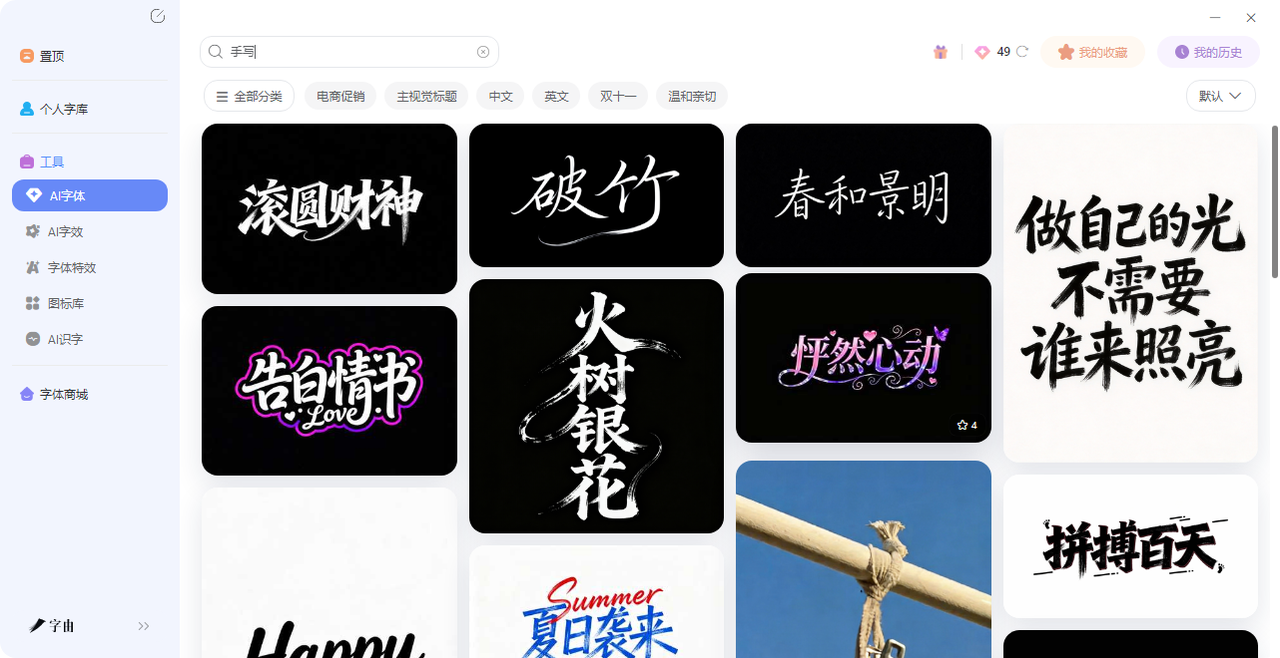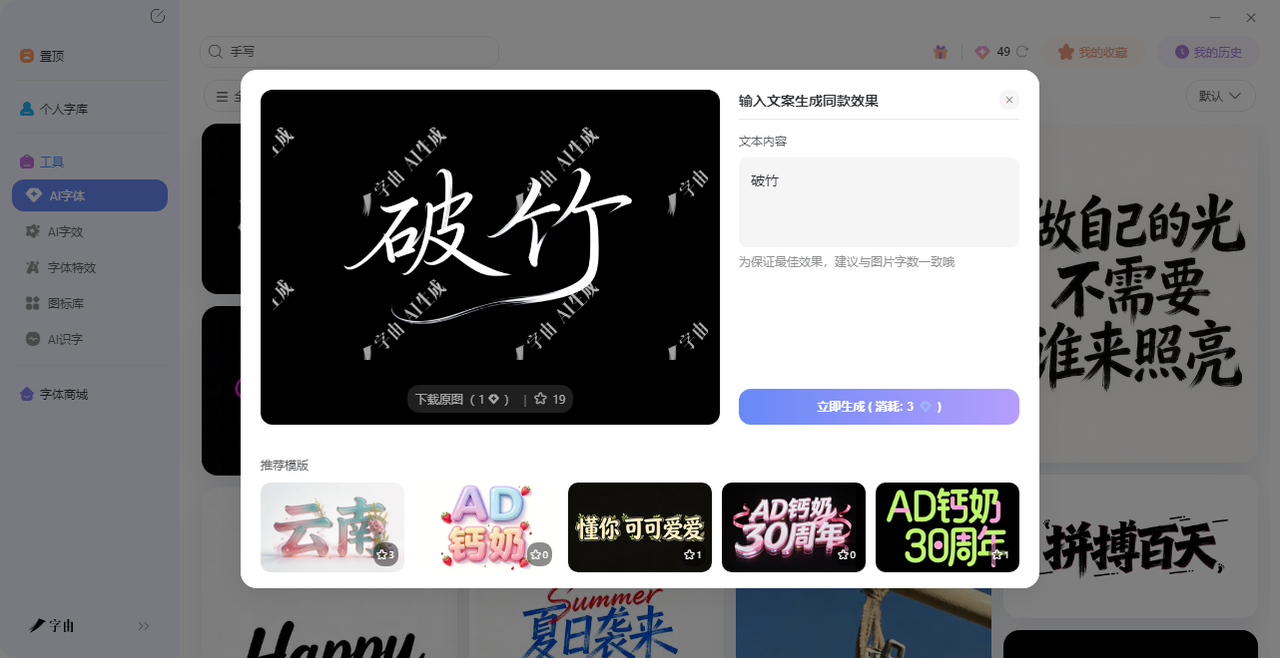
手写字体在线生成器推荐,打开网页就能立刻用
相信你有过做手账的时候,但是会担心自写不好看而影响画面整体,除了手账本,生活中也会遇到很多用到手写字体的时候,不过大部分都是手写功底跟不上想法。其实,这个问题早就有解了——现在有不少手写字体在线生成器,打开网页,输入文字,就能立刻生成各种风格的手写体。今天就把我私藏的5 个手写字体在线生成器整理出来,方便大家使用。
字由的“AI字体”功能,是我用过最顺手的手写字体在线生成器。它不只是一个字体库,更是一个能直接生成手写艺术字的工具。你不需要会书法,也不用懂设计,输入文字,选个手写模板,几十秒就能拿到一张逼真的手写体图片。
接下来我会教大家如何使用字由的AI字体:
第一步:打开字由客户端或网页版,进入【AI字体】页面。在搜索框里输入“手写”“毛笔”“墨迹”“笔触”,系统会筛出一批带着手写痕迹的模板。这些模板不是单纯的字体,而是把文字做成了像用毛笔、钢笔、水彩笔写出来的效果——有墨迹的浓淡,有笔锋的飞白,有纸纹的肌理。
第二步:每个模板都有预览图,点进去能看到细节。比如有一个模板模仿毛笔行书,笔画连笔很流畅,边缘有飞白效果;另一个像蘸水钢笔写的小字,清秀工整。选好模板,把模板里的示例文字换成你自己的文案(比如“春日来信”“见字如面”),最好和模板字数保持一致。这些模板的分类很细:做手账有“手账风”,做贺卡有“温馨手写”,做书法标题有“毛笔行书”。每个模板还支持微调——可以改颜色、调背景、甚至调整文字的倾斜角度。不满意就换一个,总有一款能对上你的感觉。
第三步:生成之前,还可以在编辑页面里微调文字的位置和大小。如果模板字数和你文案不一样,AI也会尽量适配,但效果最好的还是字数一致的。每天有免费算力点,不够用的话1 元买10 点,试错成本很低。点“立即生成”,等20-30秒,就能拿到一张带手写效果的艺术字图片。下载时选透明背景,直接拖进手账APP、PS、Canva里用,不用抠图,不用调色。如果不满意,换个模板重新生成,都没关系。
然后如果还是不知道搜什么关键词的话我可以给大家推荐几个我常用的关键词,搜索出来的每一个模板都很实用:
- 毛笔行书:笔画连笔,有飞白,适合写古风句子、诗词
- 钢笔手写:线条细,工整清秀,适合写日常笔记、信笺
- 水彩笔触:边缘晕染,带水痕,适合做手账标题、文艺封面
- 硬笔手写:像中性笔写的,自然随意,适合生活记录
- 软笔楷书:介于毛笔和硬笔之间,圆润温暖
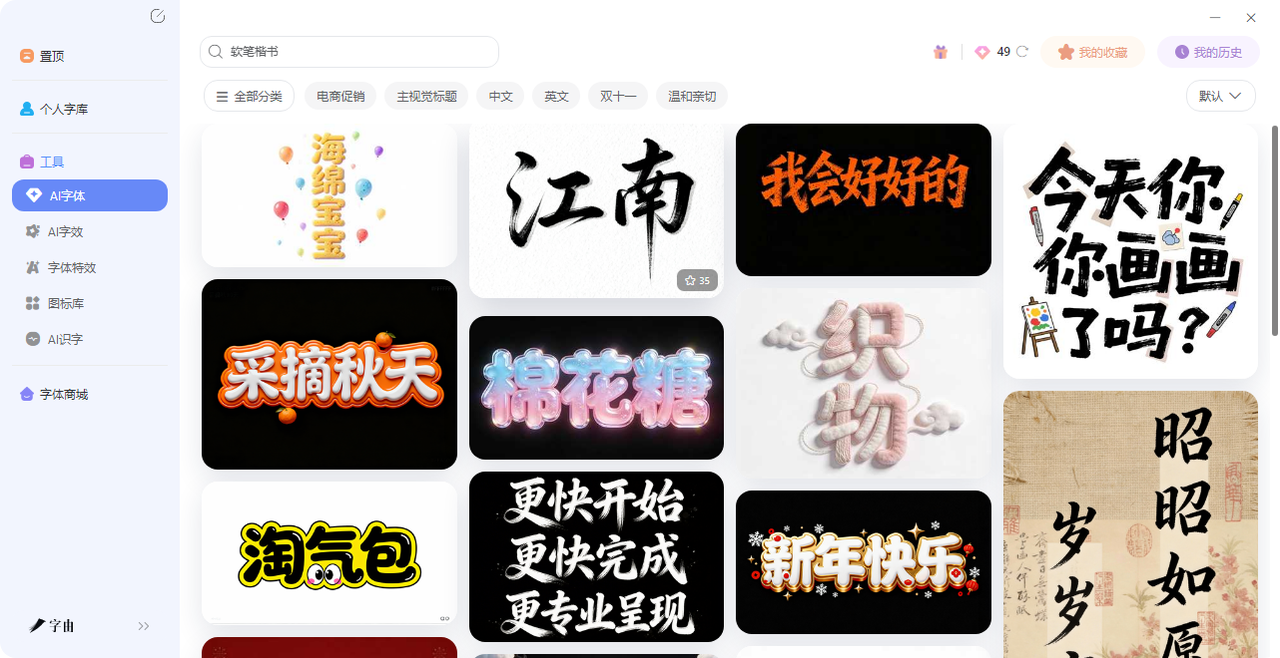
这些模板都不是基础字体,而是做好的特效效果。你不需要会书法,也不需要装字体,选个模板,填好自己想要的文案就可以了,整个过程十分简单。
2、Handwriting Font Generator
这个手写字体在线生成器提供了79 种手写样式,包括脚本体、粗体、斜体、无衬线手写等。界面左侧有样式分类,右侧是实时预览。操作也很简单:在输入框里打字,下面会自动显示所有样式的预览。你还可以调节文字大小、间距、颜色、背景,甚至加装饰、边框。喜欢的样式旁边有“Copy”按钮,点一下就能复制成Unicode 文本,直接粘贴到 Instagram、微信、微博里,不用存图片。适合需要快速把普通文字变成手写风社交文案的用户,完全免费,无需注册。比如你输入“生日快乐”,它会自动生成圆润的手写体、带花体的草书、还有像蘸水钢笔写的小字。每种风格都对应一个Unicode字符集,复制之后直接粘贴到任何地方,不会变形。
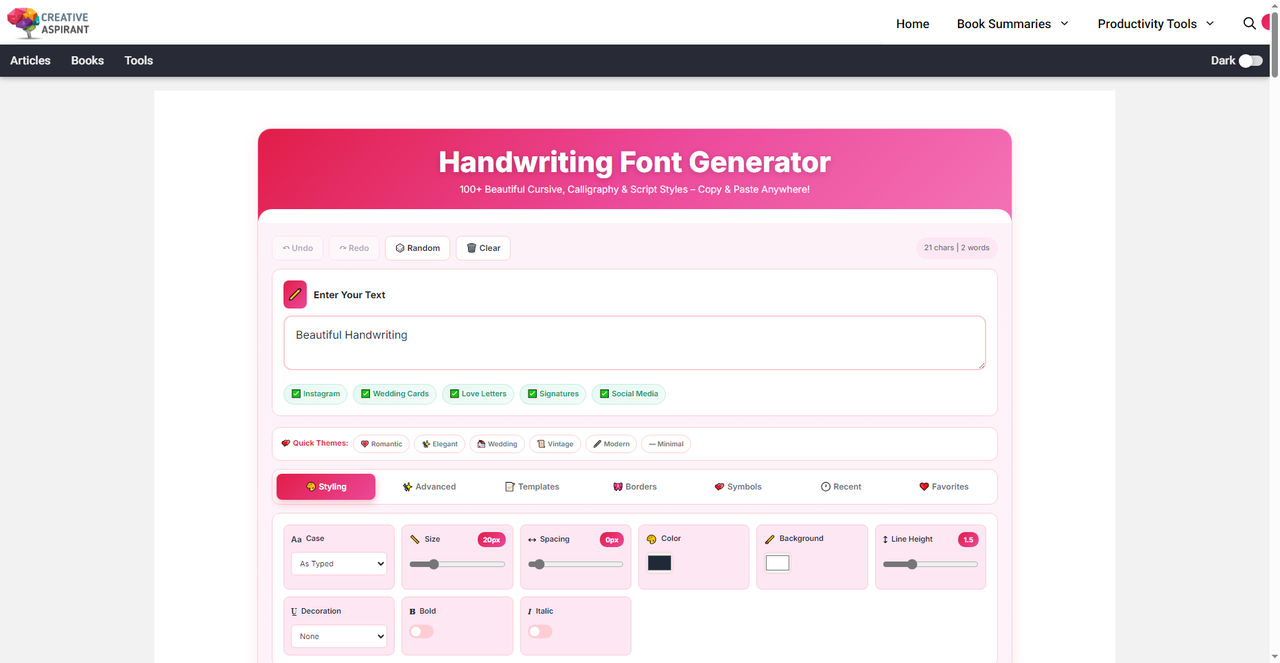
3、Fonts Generator
Fonts Generator 提供了50多种手写风格,分类有“Cursive”“Cute”“Bold”“Simple”“Decorative”等。输入文字,点击“Generate”,下面会列出所有样式,每个样式旁边有“Copy”按钮,复制后直接粘贴到任何地方。网站还提供了“Quick Themes”,比如“Romantic”“Elegant”“Wedding”“Vintage”“Modern”“Minimal”,可以快速筛选对应风格。如果你要做情书、婚礼卡片、复古海报,点一下主题就能找到合适的字体。比如点“Romantic”,出来的字体会带一点花体卷曲;点“Vintage”,字体会有复古的晕染感。每个主题下都有好几个样式,不用自己慢慢挑,一键就能找到氛围。
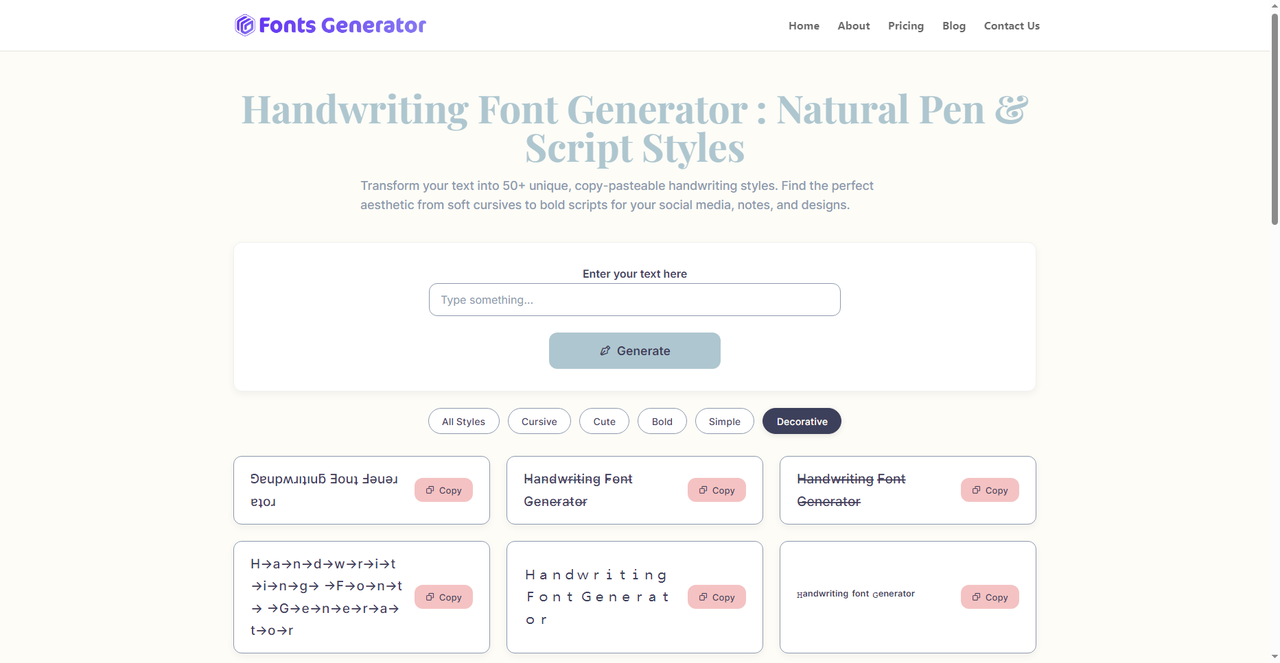
4、100LS Text to Handwriting
100LS 是一个更专业的手写字体在线生成器,专门用来把文字转换成逼真的手写文档。它有更多自定义选项:可以选择字体(比如Gloria Hallelujah),调整字体大小、墨水颜色(深黑、蓝色等),还可以选择纸张类型(白纸、横格纸、方格纸等)。生成后可以下载为图片或PDF。适合做手写笔记、作业、信件、证书等。它模拟了真实手写的效果,有墨迹深浅和纸张纹理,看起来很像真的手写。纸张类型有白纸、横格纸、方格纸、信纸四种。墨水颜色可以选黑色、蓝色、红色。生成前还能预览效果,满意了再下载。如果你做手写笔记,这个工具模拟的纸张纹理和墨迹渗透感很真实。
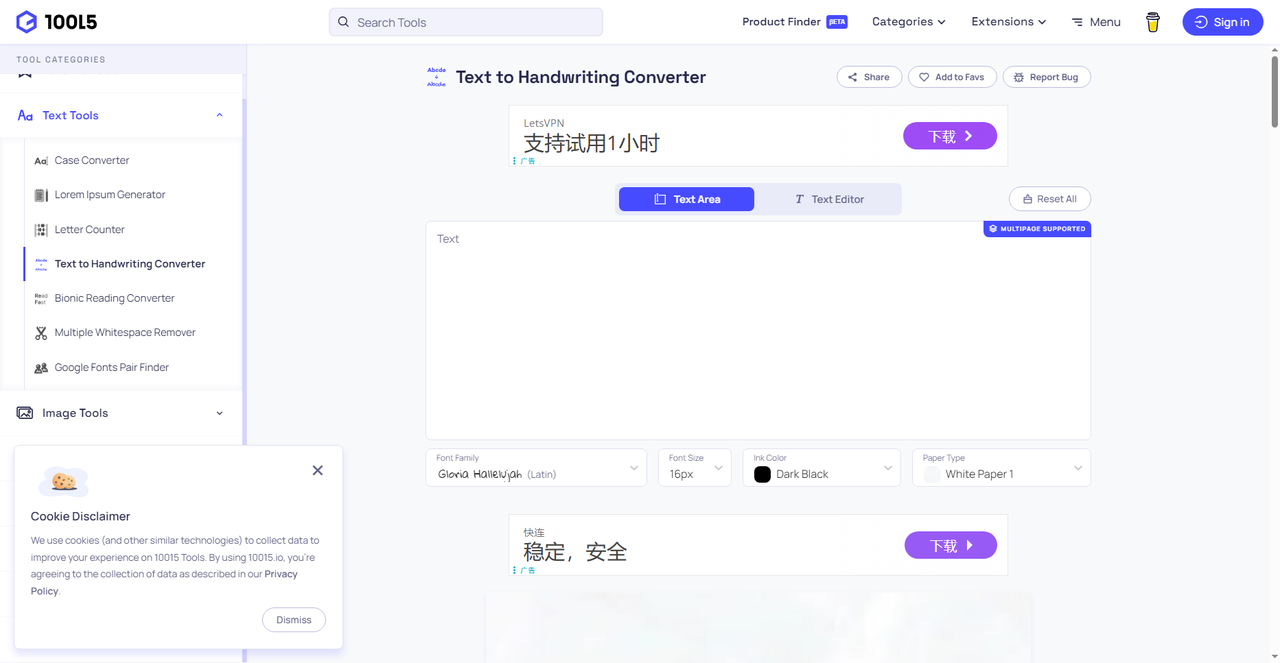
5、HandtextAI
最后一个工具功能更全面。它可以生成整页手写文档,支持多页、不同纸张格式(A4等),可调节字体、字号、行高、字间距、段落间距,还能添加阴影、背景等特效。生成后可以保存为JPG或PDF。如果你需要大段的手写文字,比如写日记、写信、做手写笔记,这个工具很适合。它的输出效果很真实,适合打印或电子存档。导出时可以选单页还是多页,分辨率也能调。支持保存为JPG或PDF,高清格式适合打印。如果你需要批量生成手写文档,这个工具比手动写快得多。
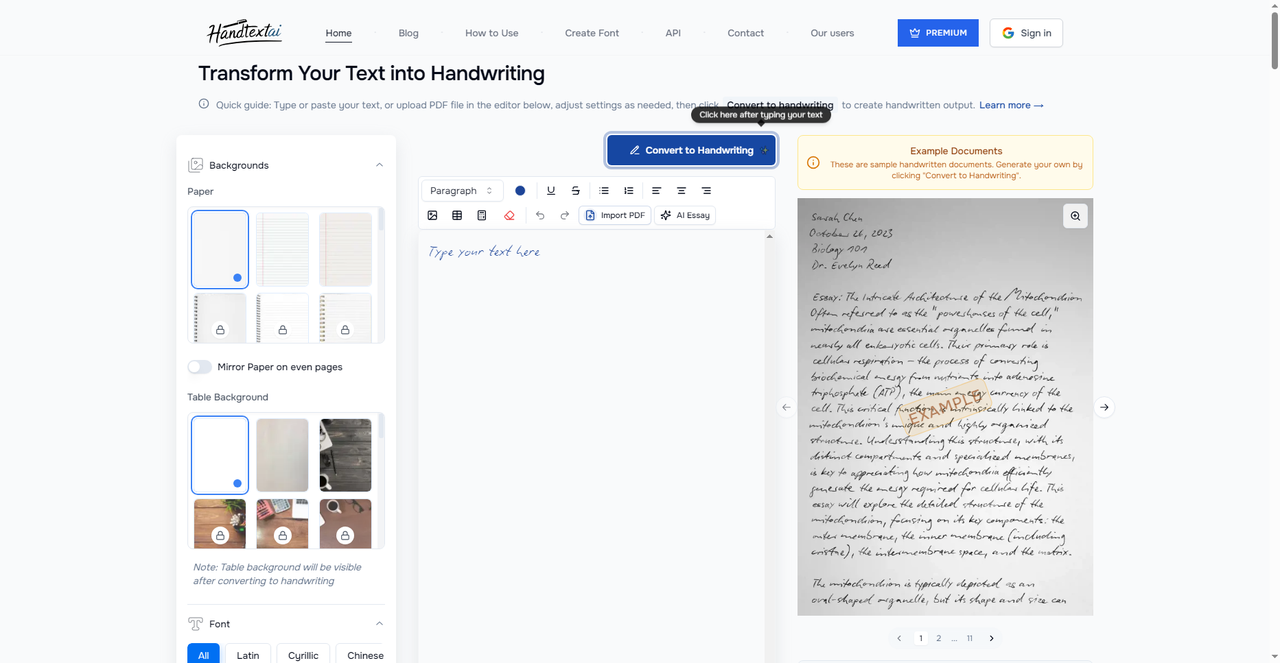
这几个手写字体在线生成器,我平时用的频率不太一样。Handwriting Font Generator 和 Fonts Generator 适合快速生成文案;100LS Text to Handwriting 和 HandtextAI 适合生成整页手写文档。又或是模仿一些手写信,也可以用来赶作业;而字由对我来说,是那个把“手写”和“设计”结合得最好的——输入文字,选个模板,几十秒就能拿到一张带笔触、墨韵的手写艺术图,拖进手账或海报里直接能用,不用再额外添加艺术效果。如果你也喜欢手写体,不妨试试字由。